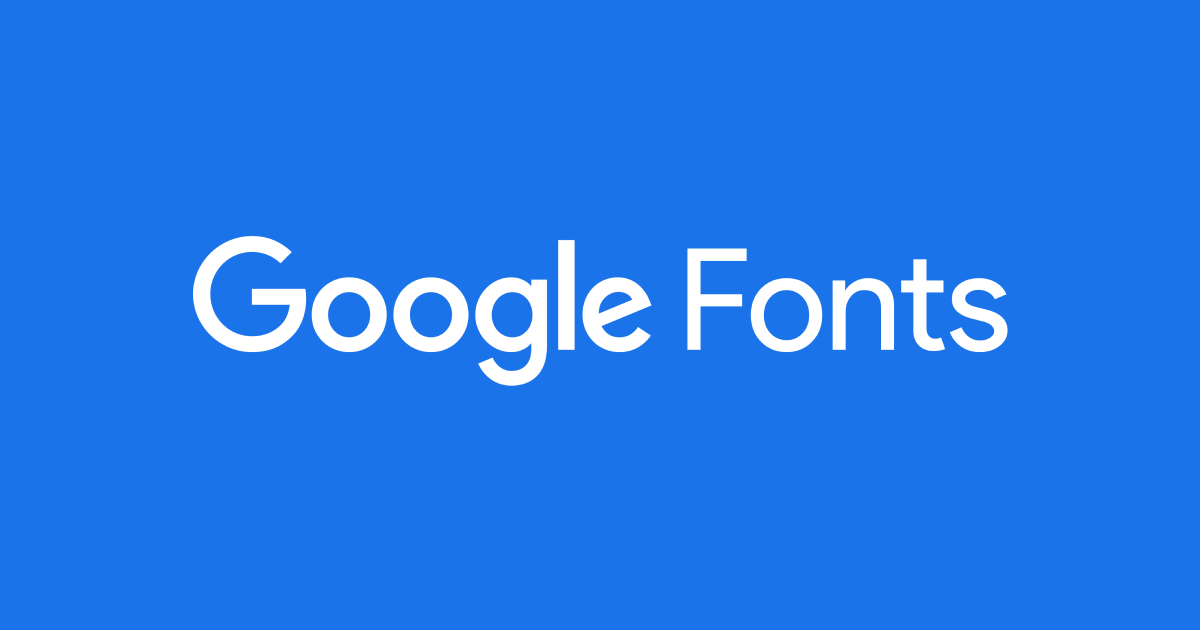
Что такое Google Шрифты? шрифты Google с бесплатными лицензиями на программное обеспечение
Вы знаете шрифты Google? Если вы устали всегда использовать одни и те же шрифты при написании документа. Или когда вы делаете какой-то дизайн? В этом случае мы рекомендуем вам совершить экскурсию по Google Fonts.
Это каталог, в котором вы найдете сотни различных дизайнов. Бесплатные шрифты, которые также регистрируются через бесплатное программное обеспечение. Таким образом, вы можете скачать их без проблем.
- 1.1 Что вы можете найти в Google Fonts, бесплатные шрифты
- 1.2 Как найти шрифт в Google Fonts
3 Как использовать шрифт из Google Fonts
Что вы можете найти в Google Fonts, бесплатные шрифты
После входа в Google Fonts вы сможете найти множество различных шрифтов, которые впоследствии сможете использовать в других программах. Прямо сейчас вы можете найти более 900 семейств шрифтов, доступных для бесплатной загрузки.
Поэтому, что бы вы ни искали, вы обязательно найдете то, что вам подходит.
Некоторые источники будут более классический, другие более веселые и другие более серьезные. Разнообразие настолько велико, что почти наверняка вы найдете то, что ищете.
Как найти шрифт в Google Fonts
Вы знаете название шрифта, который хотите скачать? В правом верхнем углу экрана вы сможете найти поисковую систему. Введя туда искомое имя, вы сможете найти, доступно ли оно.
Вам не очень ясно, что вы ищете? На главном экране вы можете найти последние тенденции. То есть шрифты, которые были загружены в последнее время.
После того, как вы выбрали знакомый шрифт, вы можете настроить его и внести в него некоторые изменения. Когда вы закончите настройку шрифта по своему вкусу, это так же просто, как скачать и установить в соответствующей программе.
Как использовать шрифт из Google Fonts
20 лучших шрифтов Google для игры в 2022 году
Все изображения предоставлены Google Fonts
Все эти великолепные шрифты можно загрузить бесплатно, и вы можете делать с ними все, что хотите: никаких условий!
Бесплатные шрифты великолепны, и в Интернете их тысячи на выбор. Проблема, однако, в том, что большинство из них можно использовать слишком часто или не впечатлять. Итак, как вы можете сэкономить деньги на шрифте, сохраняя при этом высокое качество, которое вы ожидаете от платного актива? Два слова: шрифты Google.
Впервые запущенный в 2010 году, Google Fonts представляет собой репозиторий для типографских проектов с открытым исходным кодом, и они, как правило, очень высокого качества.
Кроме того, вы можете использовать Google Fonts как в личных, так и в коммерческих проектах. Вы можете изменять их без разрешения и использовать их в дизайне логотипов для клиентов и в любом продукте, который вы продаете.
С технической точки зрения Google Fonts также очень легко использовать в Интернете. Вместо того, чтобы возиться с несколькими файлами шрифтов, вы можете использовать Google Fonts CSS API для встраивания шрифтов непосредственно на свой веб-сайт. И они легкие и сжатые, поэтому загружаются хорошо и быстро.
Как выбрать
Так как же выбрать лучший шрифт Google для своего проекта? Во-первых, вам нужно проверить, подходит ли он для используемых вами элементов дизайна. Некоторые шрифты, например, подходят для основного текста нормального размера, но не для больших заголовков, и наоборот.
Вы также захотите знать, что семейство шрифтов содержит все необходимые вам функции. Например, доступен ли шрифт в достаточном диапазоне начертаний и начертаний? Вам требуется поддержка нескольких языков, чисел, дробей и т. д.?
Вам также необходимо учитывать разборчивость: стоит, например, сравнить O и 0, l и 1, чтобы увидеть, насколько они различимы. И если вам нужна большая гибкость дизайна, есть ли несколько вариантов ширины и оптических размеров (разные версии шрифта, предназначенные для использования в разных размерах) или шрифт доступен как вариативный шрифт?
Имея все это в виду, вот наш выбор из 20 отличных шрифтов Google для начала работы. Их можно загрузить бесплатно и быстро, без каких-либо обязательств, так почему бы не попробовать их все?
1. DM Sans от Colophon
DM Sans — это низкоконтрастный геометрический шрифт без засечек, предназначенный для использования в тексте меньшего размера. Он был разработан Colophon как развитие латинской части ITF Poppins Джонни Пинхорна.
Он поддерживает расширенный набор глифов Latin, что позволяет набирать текст для английского и других западноевропейских языков.
Space Grotesk — пропорциональный шрифт без засечек, основанный на семействе фиксированной ширины Space Mono от Colophon (2016 г.). Первоначально разработанный Флорианом Карстеном в 2018 году, он сохраняет характерные детали моноширинного экрана и оптимизирован для улучшения читаемости при размерах, не связанных с дисплеем.
3. Inter by Rasmus Andersson
Созданный шведским разработчиком программного обеспечения Расмусом Андерссоном, Inter представляет собой вариативный шрифт, разработанный для компьютерных экранов, отличающийся большой высотой по оси x для облегчения чтения текста в смешанном и нижнем регистре. Он также включает в себя несколько функций OpenType, в том числе табличные числа, контекстные альтернативы, которые настраивают пунктуацию в зависимости от формы окружающих глифов, и ноль с косой чертой, когда вам нужно устранить неоднозначность нуля из буквы O.
4. Eczar от Vaibhav Singh
Eczar разработан, чтобы оживить и оживить набор нескольких шрифтов на латыни и деванагари. Обеспечивая сильное сочетание индивидуальности и производительности, как в размерах текста, так и в настройках отображения, это семейство шрифтов предлагает широкий диапазон выразительности. Демонстрационные качества дизайна усиливаются с соответствующим увеличением веса, что делает самые тяжелые веса лучше всего подходящими для заголовков и целей демонстрации.
Основанный на ранних гротесках, таких как Стивенсон Блейк, Миллер и Ричард и Бауэршен Гиссерей, Work Sans упрощен и оптимизирован для разрешений экрана. Например, диакритические знаки больше, чем они были бы напечатаны. Обычные веса оптимизированы для использования на экране текста при средних размерах (14-48 пикселей), в то время как те, что ближе к экстремальным весам, больше подходят для использования на дисплее.
6. Manrope Михаила Шаранды и Мирко Велимировича
В 2018 году Михаил Шаранда разработал Manrope, семейство современных шрифтов без засечек с открытым исходным кодом.
Кроссовер разных типов шрифта: полусжатый, полукруглый, полугеометрический, полудиновой и полугротескный. В нем используются минимальные вариации толщины мазка и полузакрытая апертура. В 2019 году Михаил сотрудничал с Мирко Велимировичем, чтобы преобразовать его в вариативный шрифт.
7. Fira от Carrois
Под руководством берлинского литейного завода Carrois, Fira разработана для интеграции с Mozilla’s FirefoxOS. В более широком смысле, это семейство шрифтов предназначено для удовлетворения потребностей в удобочитаемости большого количества телефонов, различающихся качеством экрана и визуализацией. Он поставляется в трех вариантах ширины, все они сопровождаются курсивом, а также включает вариант Mono Spaced.
8. PT Serif Александры Корольковой, Ольги Умпелевой и Владимира Ефимова
Выпущенный ParaType в 2010 году, PT Serif представляет собой панкириллицу. Переходный шрифт с засечками и гуманистическими окончаниями, он предназначен для использования вместе с PT Sans и гармонизирован по метрикам, пропорциям, весу и дизайну.
Обычный и полужирный шрифт с соответствующим курсивом образуют стандартное семейство шрифтов для основного текста. Между тем, два стиля подписи — обычный и курсив — предназначены для использования мелким шрифтом.
9. Cardo Дэвида Перри
Cardo — крупный шрифт Unicode, специально разработанный для нужд классиков, библеистов, медиевистов и лингвистов. Он также хорошо работает для общего набора в проектах, стремящихся к «старомодному» виду. Его большой набор символов поддерживает многие современные языки, а также те, которые требуются ученым. Набор шрифтов включает в себя лигатуры, цифры старого стиля, настоящие маленькие заглавные буквы и множество знаков препинания и пробелов.
Созданный аргентинской литейной компанией Impallari Type, Libre Franklin представляет собой интерпретацию и расширение классического шрифта Franklin Gothic Морриса Фуллера Бентона. Этот универсальный шрифт без засечек хорош для использования в основном тексте и заголовках, а его символы имеют характерные закругленные углы, которые становятся заметными в больших размерах.
11. Lora от Cyreal
Современный шрифт с каллиграфическими корнями, Lora хорошо подходит для использования в основном тексте. Характеризуемый умеренным контрастом, матовыми изгибами и засечками, он легко передает настроение современной истории или художественного эссе. Оптимизированный для экранов, он также хорошо работает в печати, а с 2019 года он был обновлен до вариативного шрифта..
Вдохновленный надписями Джона Баскервиля и дизайном «Scotch Roman» конца 18 века, Playfair представляет собой переходный дисплейный шрифт с высокой контрастностью и тонкими линиями. Подходит для использования в больших размерах, хорошо работает в сопровождении Georgia для основного текста.
13. Roboto Кристиана Робертсона
Roboto — это неогротескное семейство шрифтов без засечек, первоначально разработанное Google в качестве системного шрифта для операционной системы Android. У него механический скелет, а формы в основном геометрические, с дружелюбными и открытыми изгибами.
Обеспечивая естественный ритм чтения, более характерный для гуманистических шрифтов и шрифтов с засечками, обычное семейство можно использовать вместе с семейством Roboto Condensed и семейством Roboto Slab.
14. Syne by Bonjour Monde
Концептуальный дизайн Bonjour Monde и дизайн Лукаса Декруа с помощью Армана Мохтаджи. Syne изначально был разработан в 2017 году для парижского арт-центра Synesthésies. Он представляет собой исследование нетипичных ассоциаций весов и стилей и является хорошим выбором для всех, кто открыт для радикального выбора графического дизайна. Греческий шрифт, разработанный Джорджем Триантафиллакосом, был добавлен в 2022 году.
Libre Baskerville — это веб-шрифт, оптимизированный для основного текста, обычно размером 16 пикселей. Он основан на шрифте American Type Founders 19.41 классический Baskerville, но имеет более высокую x-высоту, более широкие счетчики и немного меньшую контрастность, что позволяет ему хорошо работать для чтения с экрана.
16. Anek by Ek Type
Anek – это новая интерпретация индийских традиций письма. В наиболее сжатом виде капсульные формы сохраняют компактность структур, обеспечивая графическую текстуру. На широком конце спектра дополнительное пространство для ног позволяет каждой букве зевать и растягиваться в свое сообщение. А при самом жирном начертании он идеально подходит для заголовков и словесных знаков. Анек поставляется в 10 сценариях: бангла, деванагари, каннада, латынь, гуджарати, гурмукхи, малаялам, одия, тамильский и телугу.
17. Quicksand от Эндрю Паглинавана
Созданный Эндрю Паглинаваном в 2008 году с использованием геометрических фигур в качестве основной основы, Quicksand представляет собой акцидентный шрифт без засечек с закругленными концами. Его лучше всего использовать для отображения, но он остается достаточно разборчивым, чтобы использовать его и в небольших размерах. В 2016 году он был тщательно переработан Томасом Джокином, а в 2019 году Мирко Велимирович преобразовал его в вариативный шрифт.
18. Баклан Кристиана Тальмана
Cormorant — семейство акцидентных шрифтов с засечками, вдохновленное рисунками Клода Гарамона XVI века. Он включает в общей сложности 45 файлов шрифтов, охватывающих девять различных визуальных стилей и пять весов. Cormorant — это стандартная версия, Cormorant Garamond имеет более крупные счетчики, Cormorant Infant имеет одноэтажные буквы a и g, Cormorant Unicase сочетает строчные и прописные формы, а Cormorant Upright имеет курсивное начертание.
19. Alegreya Хуана Пабло дель Пераля, Huerta Tipográfica
Alegreya — шрифт для литературы. Он передает динамичный и разнообразный ритм, облегчающий чтение длинных текстов и переводящий дух каллиграфического письма на современный типографский язык. Это «суперсемейство», которое включает в себя как семейства с засечками, так и семейства без засечек, обеспечивает сильный и гармоничный текст.
20. Poppins от Indian Type Foundry
Poppins — геометрический шрифт без засечек с поддержкой систем письма деванагари и латиницы.
Многие из латинских глифов, такие как амперсанд, более построены и рационалистичны, чем обычно, в то время как дизайн деванагари является первым шрифтом с диапазоном веса в этом жанре. Оба основаны на чистой геометрии, особенно на кругах. Каждая буквенная форма почти монолинейна, с оптическими коррекциями, применяемыми к стыкам штрихов, где это необходимо для сохранения ровного типографского цвета.
10 шрифтов Google, которые должен знать каждый веб-дизайнер | by Emily Nobbs
Создавайте современные дизайны с самыми популярными шрифтами в Интернете
Фото Артура Осипяна на Unsplash Google Fonts — одно из самых популярных мест в Интернете, где можно найти высококачественные шрифты. Это отличный ресурс для поиска бесплатных шрифтов для личного и коммерческого использования. С более чем 900 на выбор поиск идеального шрифта для вашего дизайна иногда может быть сложным и трудоемким. К счастью, с помощью Google Fonts Analytics мы можем увидеть самые популярные шрифты на платформе по общему количеству просмотров.
Просматривая самые просматриваемые шрифты за последний год, мы можем узнать о последних тенденциях в типографике и выбрать проверенные шрифты для наших собственных проектов. Здесь мы рассмотрим десять лучших шрифтов Google и различные стили каждого из них. Каждый шрифт сохранил свою популярность, будучи доступным и универсальным во многих областях. Итак, продолжайте читать, чтобы найти вневременной шрифт для вашего следующего проекта, каким бы он ни был.
Дизайнер: Кристиан Робертсон
Описание: Робот имеет двойственную природу. У него механический скелет, а формы в основном геометрические. В то же время шрифт отличается дружелюбными и открытыми изгибами. В то время как некоторые гротески искажают формы букв, чтобы добиться жесткого ритма, Roboto не идет на компромиссы, позволяя буквам принимать их естественную ширину. Это обеспечивает более естественный ритм чтения, более характерный для гуманистических шрифтов и шрифтов с засечками.
Это обычное семейство, которое можно использовать вместе с семейством Roboto Condensed и семейством Roboto Slab.
Дизайнер: Стив Маттесон
Описание: Open Sans — гуманистический шрифт без засечек, разработанный Стивом Маттесоном, директором по шрифтам Ascender Corp. Эта версия содержит полный набор из 897 символов, включая стандартную ISO Latin 1, Наборы латинских символов CE, греческих и кириллических. Open Sans был разработан с вертикальным акцентом, открытыми формами и нейтральным, но дружелюбным внешним видом. Он был оптимизирован для печати, Интернета и мобильных интерфейсов и имеет отличные характеристики разборчивости букв.
Дизайнер: Łukasz Dziedzic
Описание: Lato — это семейство шрифтов без засечек, созданное летом 2010 года варшавским дизайнером Лукашем Дзеджичем («Lato» означает «Лето» на польском языке). В декабре 2010 года семейство Лато было опубликовано под лицензией Open Font License его литейной компанией tyPoland при поддержке Google.
За последние десять или около того лет, в течение которых Лукаш занимался шрифтовым дизайном, большинство его проектов были связаны с конкретной дизайнерской задачей, которую ему нужно было решить. С Лато все было по-другому. Изначально семейство задумывалось как набор корпоративных шрифтов для крупного клиента — который в итоге решил пойти в другом стилистическом направлении, поэтому семейство стало доступным для публичного релиза.
Работая над Лато, Лукаш пытался тщательно сбалансировать некоторые потенциально конфликтующие приоритеты. Он хотел создать шрифт, который казался бы довольно «прозрачным» при использовании в основном тексте, но отображал бы некоторые оригинальные черты при использовании в больших размерах. Он использовал классические пропорции (особенно заметные в верхнем регистре), чтобы придать формам букв знакомую гармонию и элегантность. В то же время он создал гладкий шрифт без засечек, который делает очевидным тот факт, что Lato был разработан в 2010 году, хотя он не соответствует какой-либо современной тенденции.
Полукруглые детали букв придают Lato ощущение тепла, а прочная структура обеспечивает стабильность и серьезность. «Мужчина и женщина, серьезные, но дружелюбные. С ощущением лета», — говорит Лукаш. Узнайте больше на www.latofonts.com
Дизайнер: Джульета Улановски
Описание: Старые плакаты и вывески в традиционном районе Монтсеррат в Буэнос-Айресе вдохновили Джульетту Улановски на разработку этого шрифта и спасение городской красоты. Типографика, возникшая в первой половине ХХ века. По мере того, как городское развитие меняет это место, оно никогда не вернется к своей первоначальной форме и навсегда потеряет такие особенные и уникальные замыслы. В буквах, вдохновивших этот проект, есть работа, самоотверженность, забота, цвет, контраст, свет и жизнь, день и ночь! Это те типы, которые делают город таким красивым. Проект Монтсеррат начался с идеи спасти то, что находится в Монтсеррате, и освободить его под свободной лицензией SIL Open Font License.
Это обычная семья, и пока у нее есть две сестринские семьи, Альтернативные и Субраяда. Многие формы букв являются особыми в семействе Alternates, в то время как «Subrayada» означает «подчеркнутый» на испанском языке и отмечает особый стиль подчеркивания, который интегрирован в формы букв, найденные в районе Montserrat .
Дизайнер: Кристиан Робертсон
Описание: Робот имеет двойственную природу. У него механический скелет, а формы в основном геометрические. В то же время шрифт отличается дружелюбными и открытыми изгибами. В то время как некоторые гротески искажают формы букв, чтобы добиться жесткого ритма, Roboto не идет на компромиссы, позволяя буквам принимать их естественную ширину. Это обеспечивает более естественный ритм чтения, более характерный для гуманистических шрифтов и шрифтов с засечками.
Это семейство Condensed, которое можно использовать вместе с обычным семейством Roboto и семейством Roboto Slab.
Дизайнер: Вернон Адамс
Описание: Oswald — это переработка классического стиля, исторически представленного шрифтами без засечек «Альтернативная готика». Персонажи Освальда изначально были перерисованы и преобразованы, чтобы лучше соответствовать пиксельной сетке стандартных цифровых экранов. Oswald предназначен для свободного использования в Интернете веб-браузерами на настольных компьютерах, ноутбуках и мобильных устройствах.
С момента первого запуска в 2011 году Вернон Адамс постоянно обновлял Oswald до 2014 года. Вернон добавил светлые и полужирные веса, поддержку большего количества языков латиницы и кириллицы, ужесточил интервалы и кернинг и внес множество уточнений глифов во всем семействе на основе сотен отзывов пользователей. В 2016 году Калапи Гаджар обновил латинскую часть семейства, чтобы завершить работу, начатую Верноном. В январе 2019 года он был обновлен осью веса переменного шрифта.
Дизайнер: Пол Д.
Хант
Описание: Source® Sans Pro, первое семейство шрифтов Adobe с открытым исходным кодом, разработанное Полом Д. Хантом. Это шрифт без засечек, предназначенный для использования в пользовательских интерфейсах.
Дизайнер: John Hudson
Описание: Slabo — это набор шрифтов определенного размера для использования в онлайн-рекламе и других целях в Интернете. В настоящее время коллекция включает этот шрифт, Slabo 27px и Slabo 13px. Каждый шрифт в коллекции точно настроен для использования с размером пикселя в его названии.
Дизайнеры: Matt McInerney, Pablo Impallari и Rodrigo Fuenzalida
Описание: Raleway — семейство элегантных шрифтов без засечек. Первоначально разработанный Мэттом Макинерни как один тонкий груз, он был расширен до семейства из 9 весов Пабло Импаллари и Родриго Фуэнзалида в 2012 году и iKerned Иджино Марини. Тщательный обзор и курсив были добавлены в 2016 году.
Это циферблат, и в загрузке представлены как старые, так и подкладочные цифры, стандартные и произвольные лигатуры, довольно полный набор диакритических знаков, а также стилистическая альтернатива, вдохновленная более геометрическими шрифты без засечек, чем набор символов по умолчанию, вдохновленный неогротеском.
У него также есть родственная семья Raleway Dots.
Дизайнер: ПараТайп
Описание: PT Sans разработан для проекта «Государственные Шрифты Российской Федерации». Также доступно второе семейство проекта, PT Serif.
Шрифты выпущены по лицензии libre и могут свободно распространяться: Основная цель проекта — дать возможность жителям России читать и писать на родном языке.
Проект посвящен 300-летию гражданского шрифта, изобретенного Петром I в 1708–1710 гг. Финансовую поддержку ему оказало Федеральное агентство по печати и массовым коммуникациям.
Шрифты включают стандартные западные, центральноевропейские и кириллические кодовые страницы, а также символы всех титульных языков Российской Федерации.